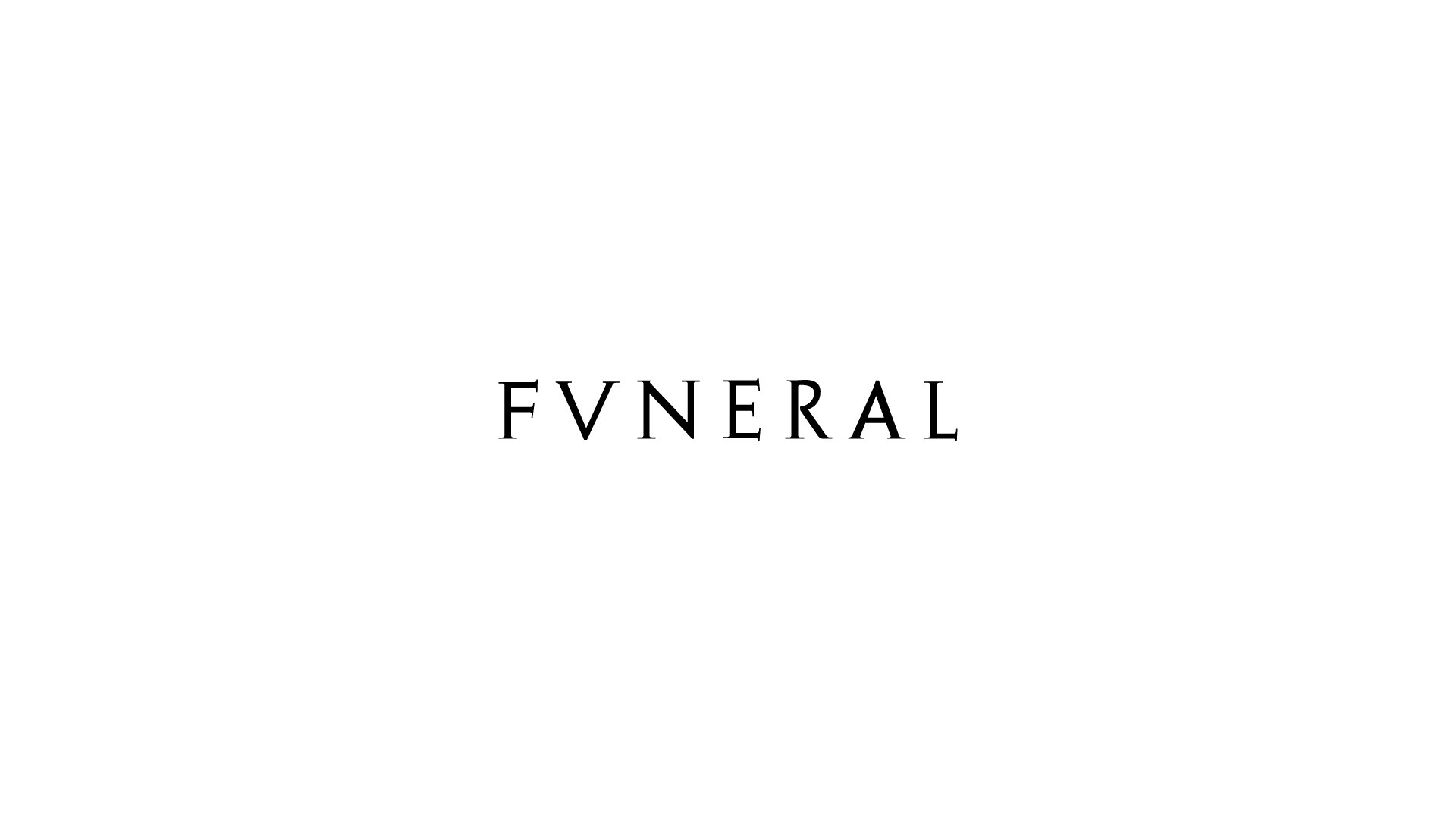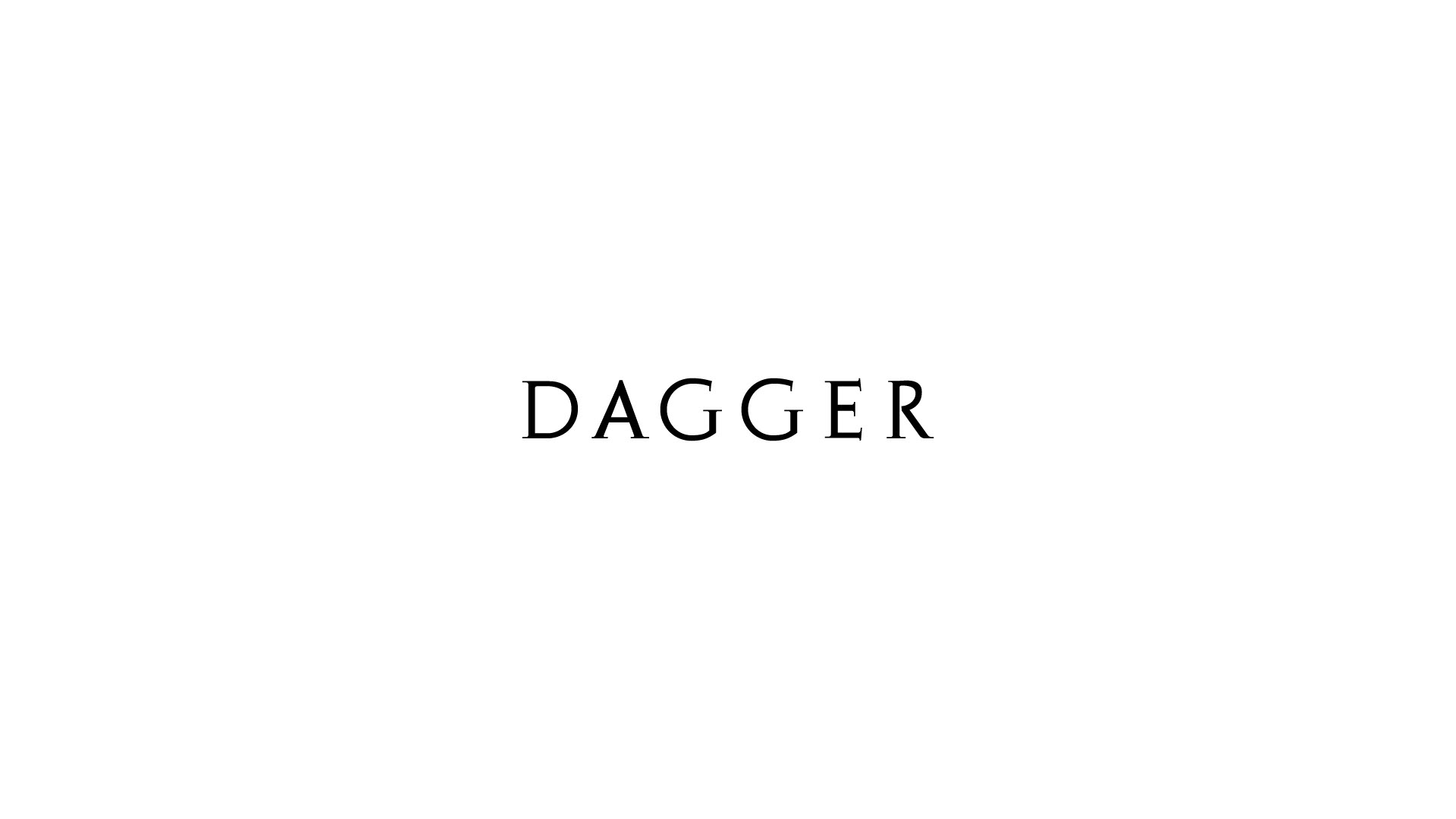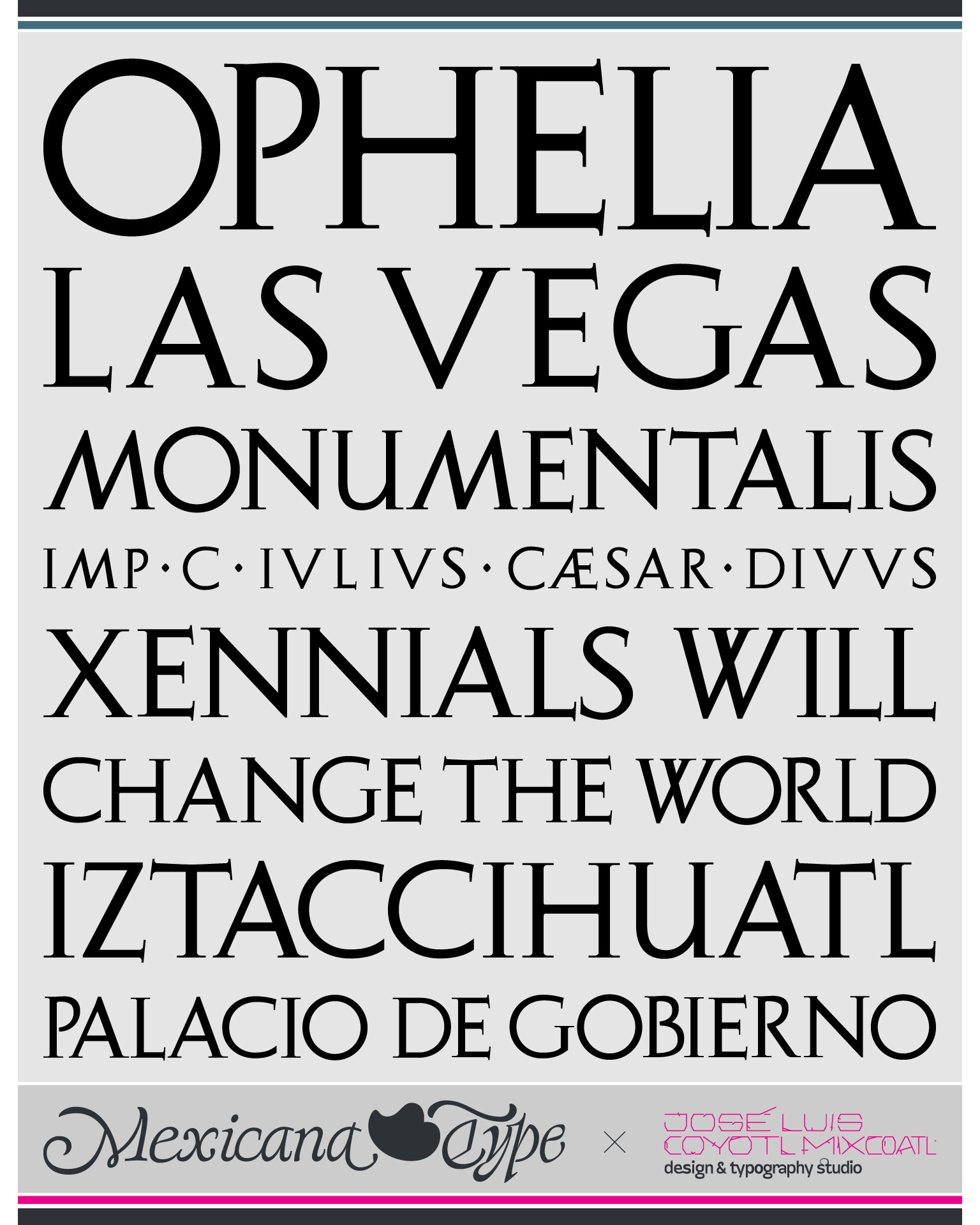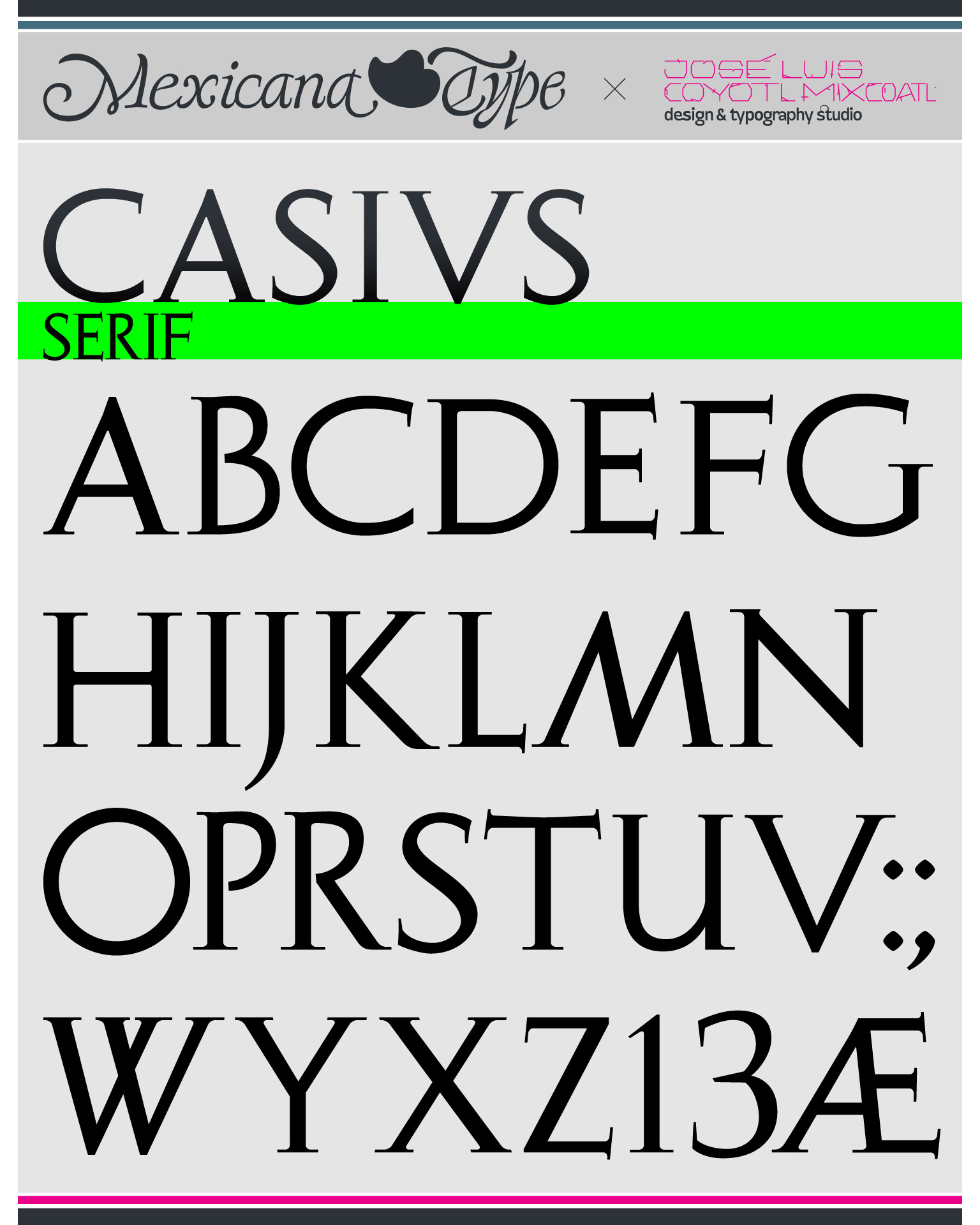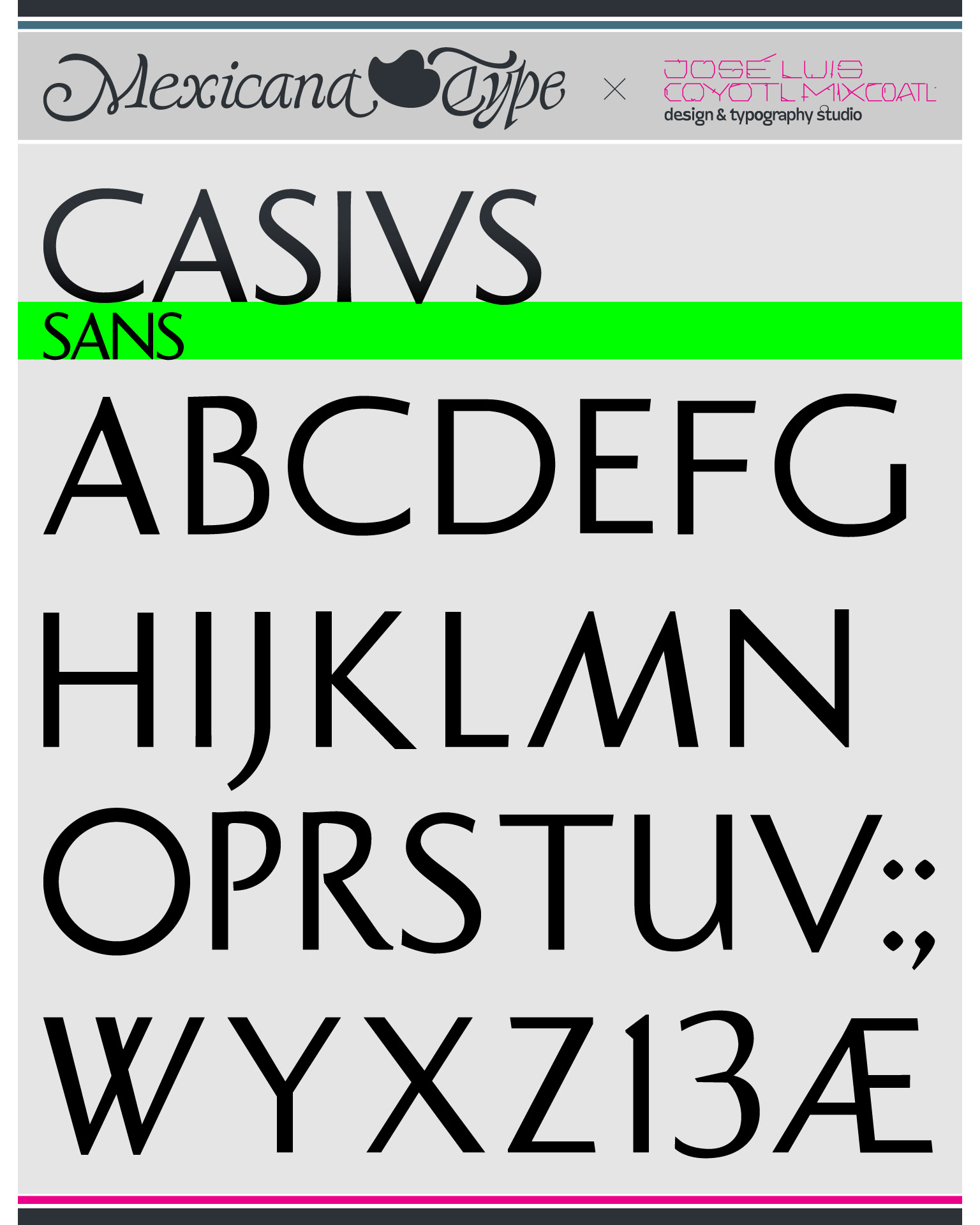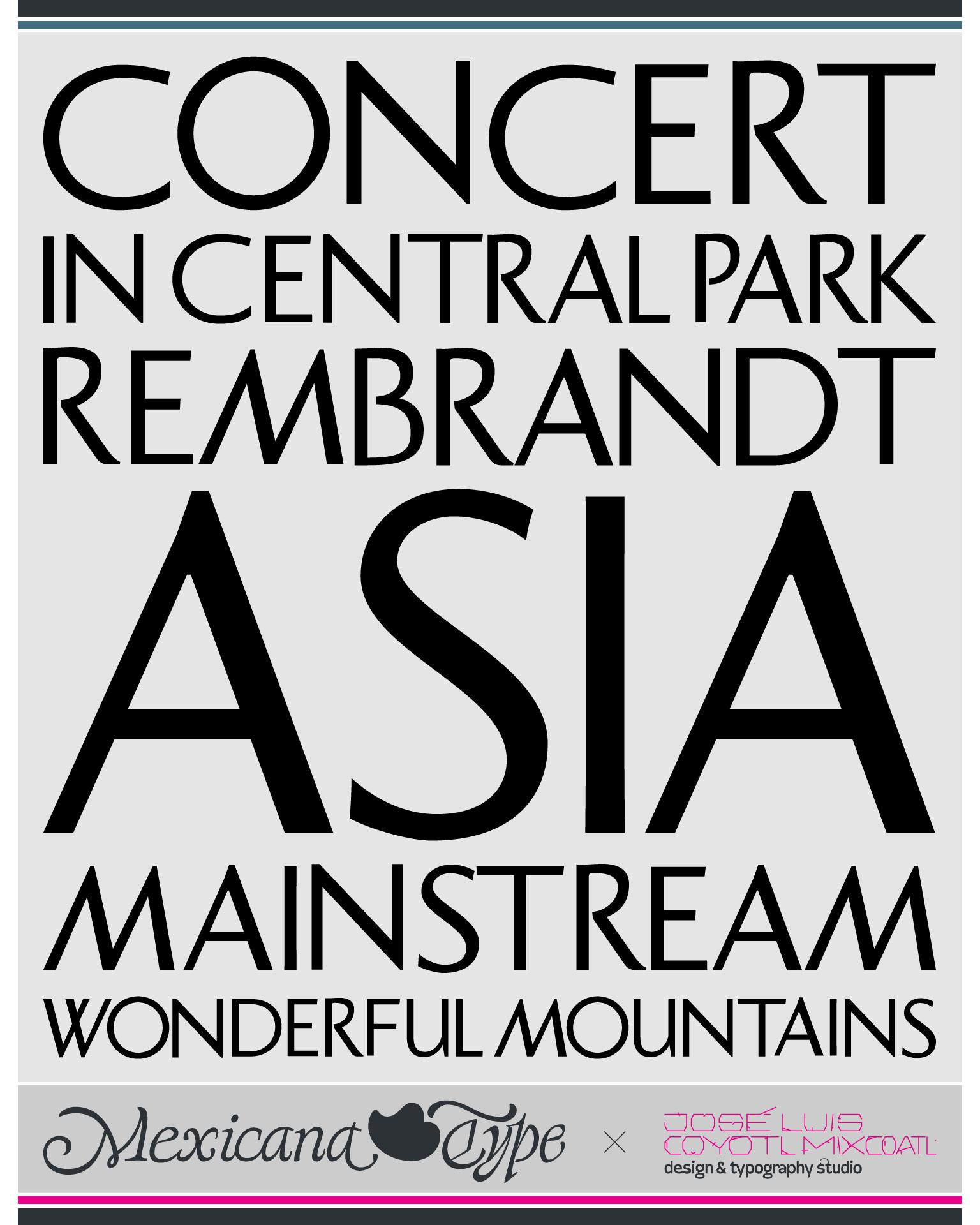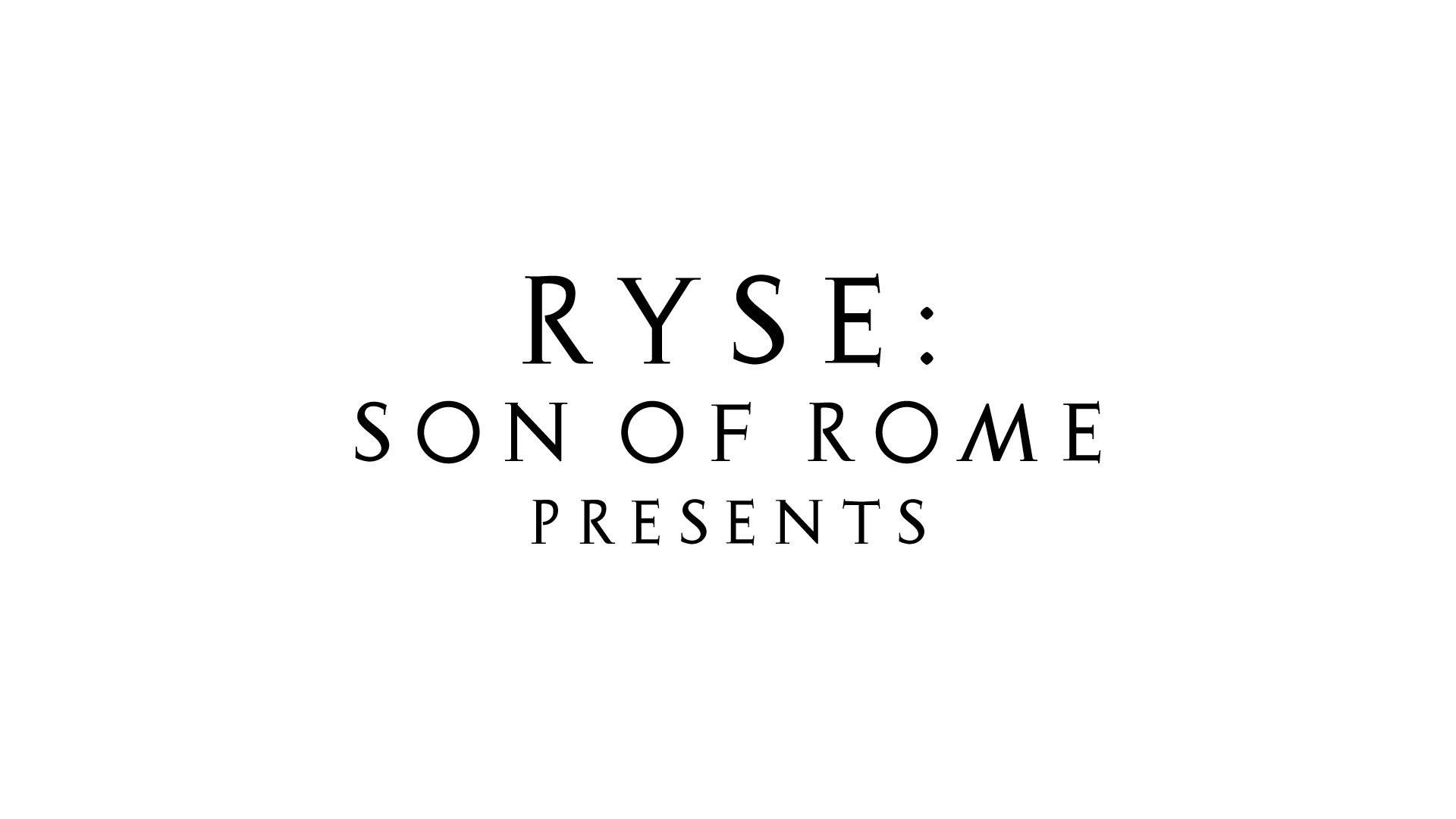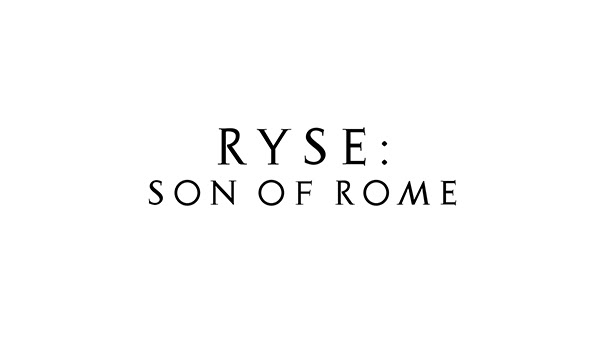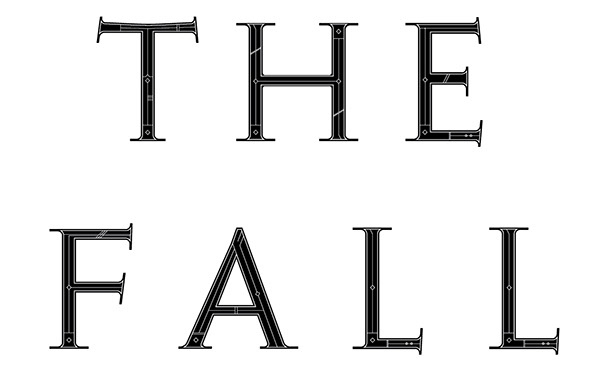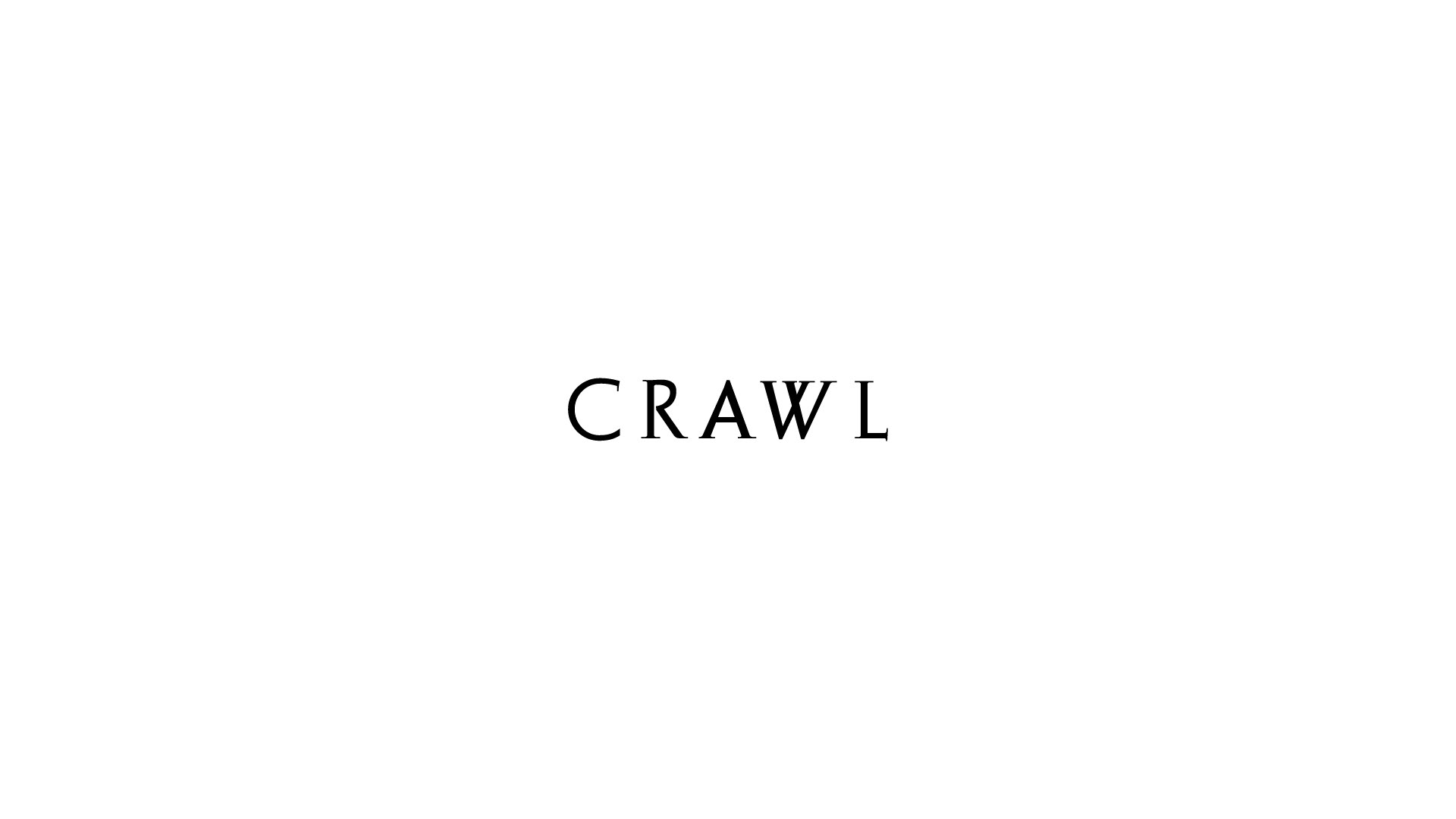
Inicialmente MxT Casius fue un custom type desarrollado en Prologue Films para un proyecto de marketing en algunos títulos para carteles para el videojuego 'Ryse', que basa su historia en la conquista del imperio Romano.
Partiendo de esa base conceptual, se desarrollo un estilo basado en el modelo de la columna de Trajano, pero con una construcción y lógica de hechura de grabado en metal, pues uno de los planteamientos sugeridos era justamente modelarlo en 3D digital para que los textos tuvieran una apariencia con elementos visuales tallados en piedra o en metal.
Se desarrollo un estilo patinado, con cierto aire modular pero como si fueran letras de un estilo histórico temprano, generando un serif muy modular y recto, sólido pero contrastado en sus remates, alejándose de la muy popular 'Trajan' de Carol Twombly, tratando de ser una versión más cruda y en proporciones completamente diferentes.
Inicialmente se desarrollaron una serie de palabras, y en ellas también se diseñaron una serie de ornamentos internos que fueran la parte que estaría grabada, remitiendo a los grabados de armería pero con un sentido un tanto más contemporáneo.
Al finalizar el proyecto de diseño en los carteles, el cliente solicitó el mismo estilo customizado para algunos otros títulos y frases, incluyendo el título pero con esta nueva tipografía dentro del videojuego, y con ello, requirió la expansión a una cantidad más amplia en su mapa de caracteres.
Varios años despues también desarrollé la version Sans, que es mucho más limpia y con un aspecto mucho más moderno y contemporáneo, que contrasta con el aire clásico de su contraparte original con serifs.